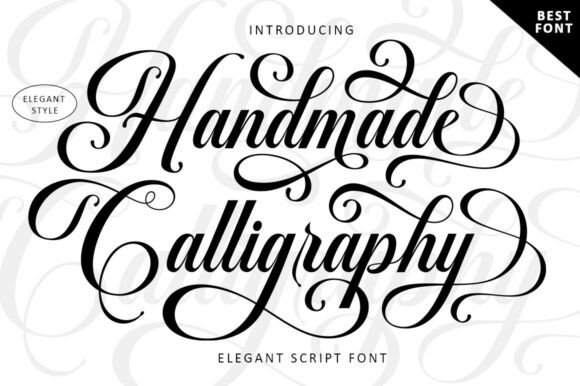
Handmade Calligraphy
適切なデザイン要素を見つけるのは難しい場合がありますが、Handmade Calligraphyは作品を即座に引き立てる優れたコレクションを提供します。
POD(オンデマンド印刷)製品、結婚式の招待状、またはソーシャルメディアのグラフィックを作成している場合でも、Handmade Calligraphyは理想的です。